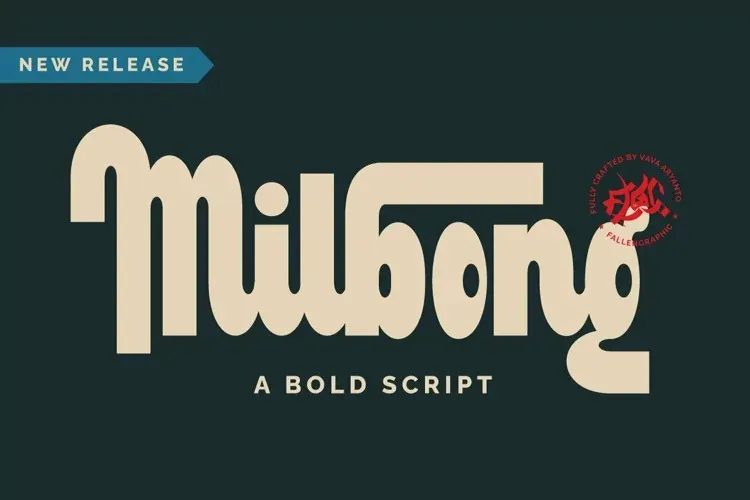
A fonte Milbong é uma viagem no tempo à estética vintage dos tempos modernos. Desenvolvida para headlines, logotipos ou desenhos visuais, essa fonte é inspirada nas marcas de sinais de lojas como bar, hotel e salões de barbeios. Ela captura o charme alegre e atemporal dessas marcas vintage, oferecendo uma maneira única de incorporar esse estilo nostálgico em designs contemporâneos. Perfeita tanto para uso digital quanto em impressão, Milbong é ideal para quem busca dar um toque especial à sua identidade visual ou projetos gráficos. Com suas linhas elegantes e personalizadas, você pode criar mensagens memoráveis que se conectam profundamente com seu público objetivo, tornando-se uma escolha irresistível em qualquer design.